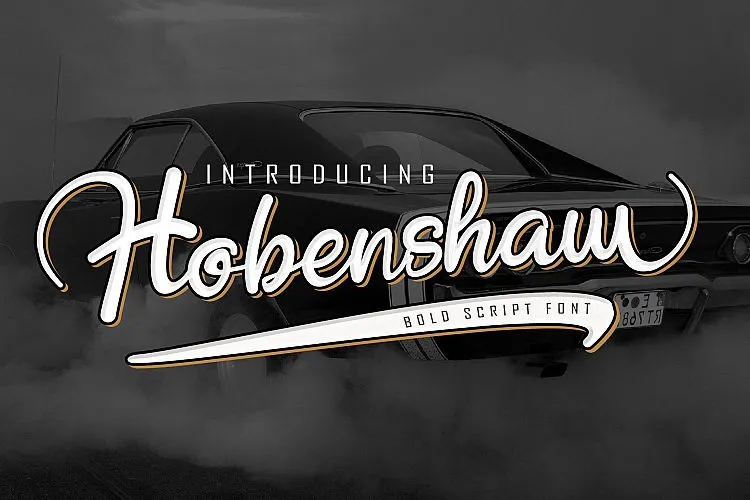
Hobenshaw Script Font – Download Grátis
Esta é uma fonte script que traz a elegância e sofisticação necessária para qualquer projeto editorial ou design criativo. Introduzimos Hobenshaw Script Font, uma criação singular do designer letterara. Com suas variações estilísticas surpreendentes, essa fonte transmite autenticidade e originalidade em cada letra, tornando-a perfeita para projetos como postais de casamento, identificações de marca, convites, citações, impressões digitais e muito mais. Com uma aparência fluida e arredondada, esta fonte conta com todas as letras maiúsculas e minúsculas padrão, acentos diacriticos, números e alternativas, garantindo flexibilidade para adaptar ao seu gosto pessoal. Hobenshaw Script Font oferece uma textura única que transmite autenticidade, permitindo-lhe criar designes únicos e personalizados. Seja você um designer de moda, uma empresa criando identificações de marca ou um casal organizando um grande evento, esta fonte é o aliado perfeito para transformar seus projetos em algo realmente único. Selecione a fonte ideal que reflete sua identidade pessoal e deixe-se levar pela elegância fluida dessa fonte script poderosa.